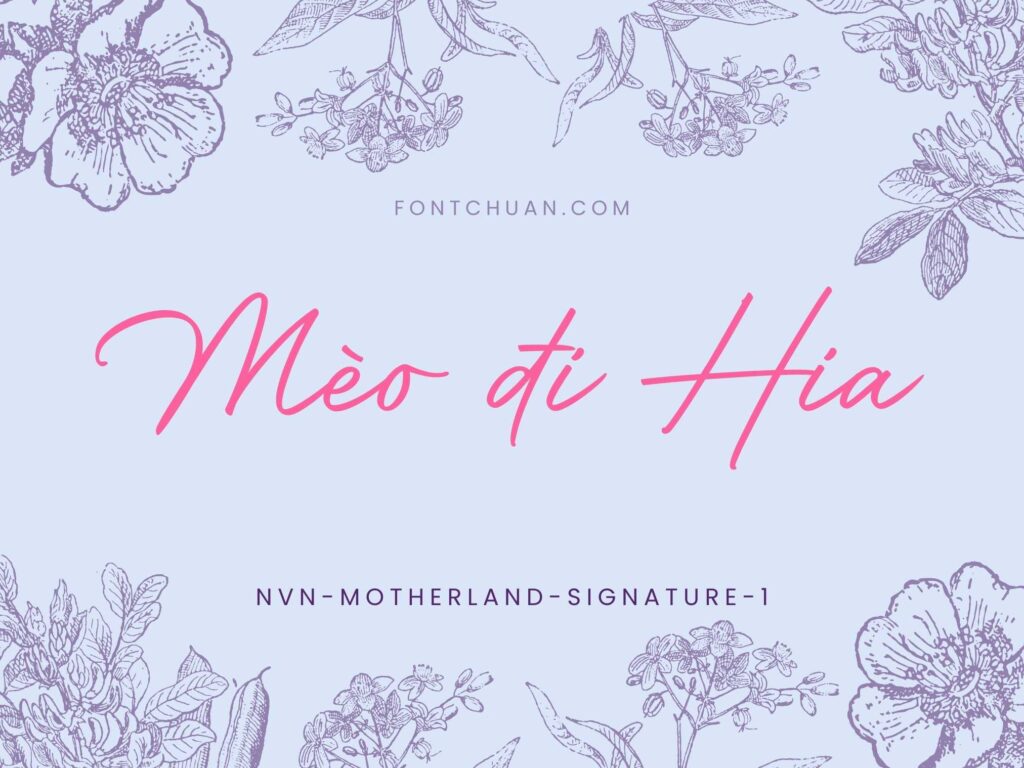
Font NVN Motherland Signature Việt Hóa
Motherland Signature là một font chữ viết tay thanh lịch, được thiết kế bởi Hendra Pratama và phát hành trên Creative Market. Font này mang phong cách hiện đại, tinh tế với nét chữ mềm mại, phù hợp cho nhiều mục đích thiết kế từ cá nhân đến thương mại. Phiên bản Motherland Signature này đã được Việt hóa bởi NVN Font, giúp hỗ trợ đầy đủ các ký tự tiếng Việt, mang lại trải nghiệm gõ chữ trọn vẹn hơn cho người dùng. Ngoài tiếng Việt, font còn hỗ trợ nhiều ngôn ngữ khác, mở rộng khả năng ứng dụng trên phạm vi quốc tế. Font được thành viên của Font Chuẩn chọn lọc và sưu tầm nhằm đáp ứng nhu cầu bạn đọc và giúp áp dụng vào các dự án thiết kế thực tế.
Về đặc điểm thiết kế, Motherland Signature thuộc loại font script với đường nét mềm mại, tự nhiên như chữ viết tay thật. Font có độ dày vừa phải, độ tương phản tinh tế, giúp tăng tính thẩm mỹ và dễ đọc. Các ligatures và ký tự thay thế được thiết kế chỉn chu, tạo sự kết nối liền mạch giữa các chữ cái. Với phong cách sang trọng và sáng tạo, Motherland Signature đặc biệt phù hợp với các ứng dụng như thiết kế logo, danh thiếp, bao bì mỹ phẩm, bìa sách, tiêu đề quảng cáo và các sản phẩm thương hiệu cá nhân. Ngoài ra, font này còn là một font valentine lý tưởng cho thiệp mời và các dự án sáng tạo cần sự mềm mại, nghệ thuật. Về ngành nghề, Motherland Signature thường được sử dụng trong lĩnh vực quảng cáo, spa, ẩm thực, thiệp cưới và ảnh cưới. Sự tinh tế và nét chữ uyển chuyển giúp font này dễ dàng hòa nhập vào nhiều phong cách thiết kế từ cổ điển đến hiện đại.